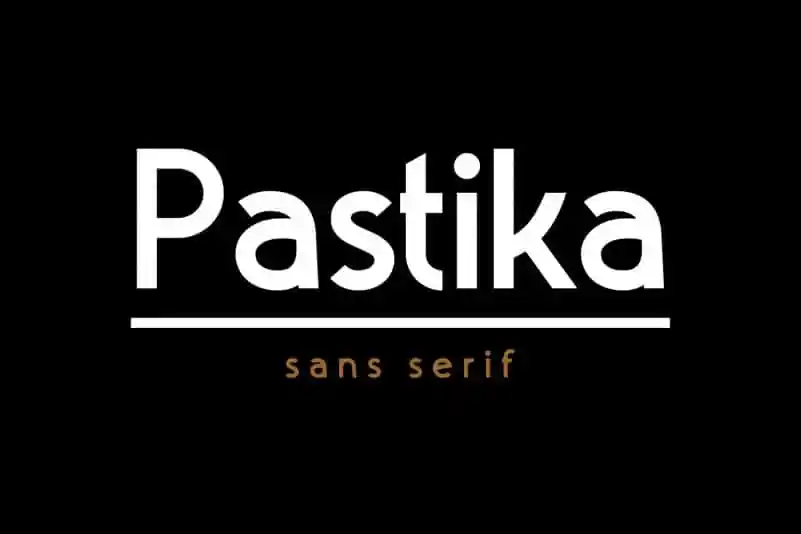
Pastika - Classic Sans Font
Pastika é uma família de fontes sans serif que traz um toque de modernidade para seus projetos digitais e impressos. Suave mas robusta, esta fonte foi projetada para atender a uma ampla gama de necessidades gráficas. Perfeita para criar marcas de marca, embalagens de produtos, convites, citações, estampas de camisetas, rótulos, posters e logotipos – Pastika é versátil o bastante para abraçar todos esses formatos criativos. A madeDeduk foi o responsável por essa elegante família de letras. Suas linhas retas e minimalistas proporcionam um equilíbrio harmonioso entre funcionalidade e estética, tornando-se uma opção confiável para designers profissionais e amadores que buscam fontes modernas e limpas para seus projetos. A simplicidade de Pastika não se traduz em falta de expressividade; ao contrário, ela proporciona um fundo sólido para os elementos gráficos, permitindo que eles floresçam de forma criativa. Para aqueles buscando uma fonte moderna e elegante sem perder a essência do tipo serif, Pastika é o ideal. Com um design limpo e profissional, ela se torna a escolha perfeita para quem deseja dar um toque sofisticado aos seus trabalhos. Pastika é mais que uma fonte; é uma aliada eficaz em qualquer projeto que você esteja criando.